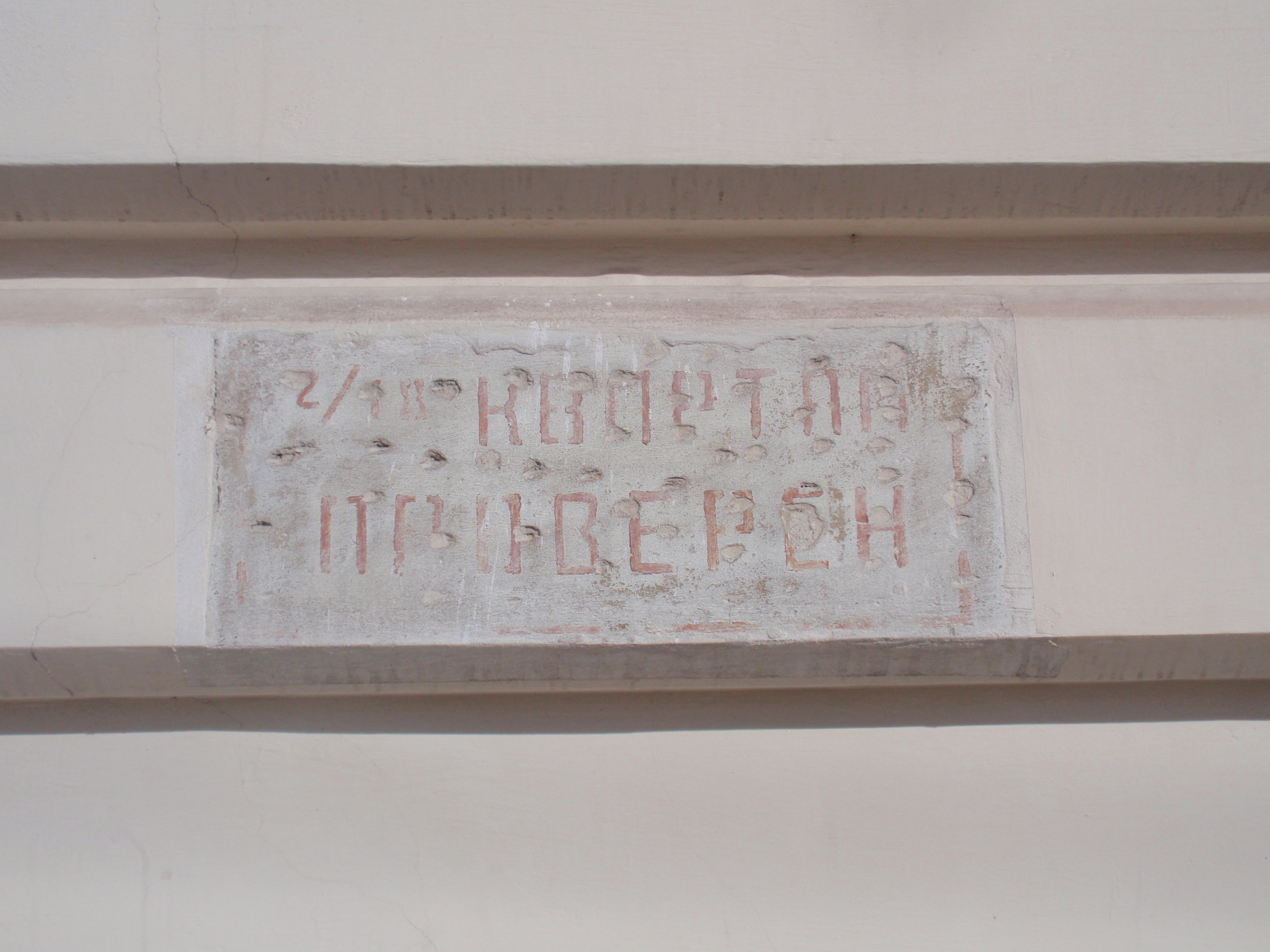
Spuren von 1945
Diese Zeichen finden sich am Palais Pallavicini auf dem Josephsplatz. Der Text ist russisch und heißt "Kwartal proweren", das bedeutet: "Der Häuserblock ist überprüft". So haben sowjetische Soldaten nach Kriegsende 1945 jene Ecken in der Stadt markiert, in denen sie keine Minen, Pulverlager o.ä. gefunden hatten.